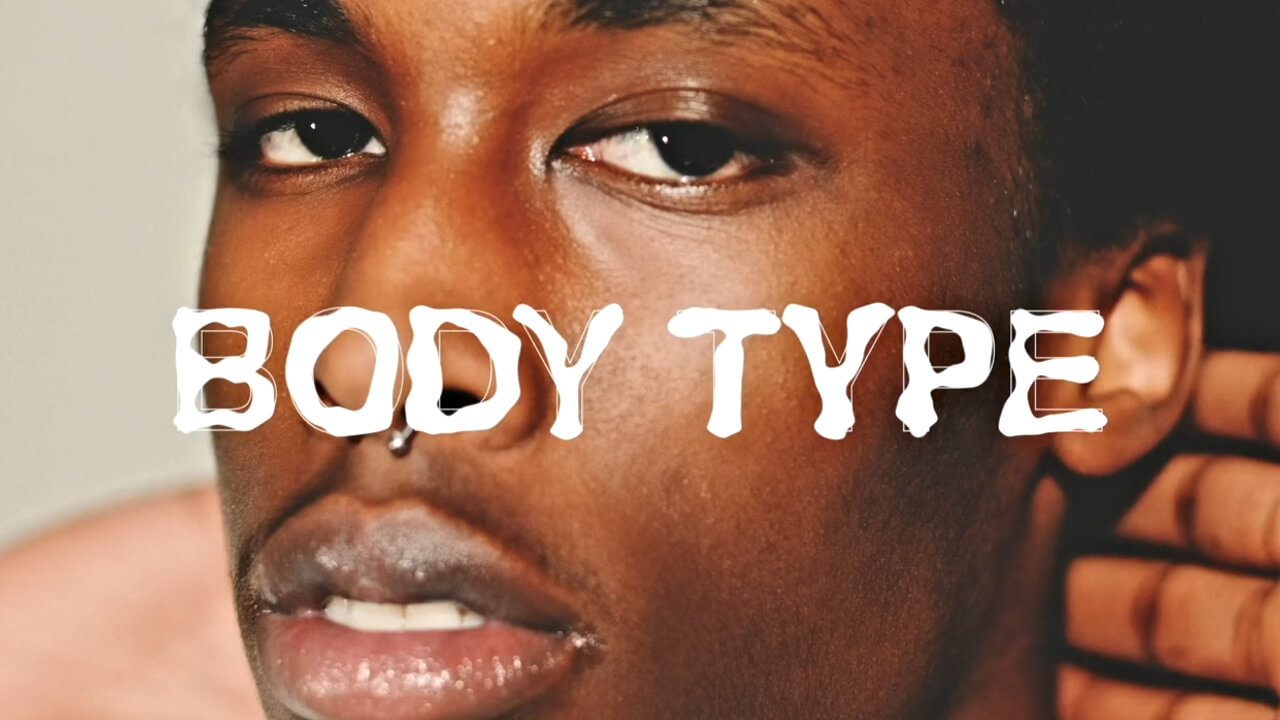
La belleza ha estado marcada históricamente por unos cánones concretos, que se han ido estrechando a raíz de la globalización y la expansión de los medios de comunicación. Una tendencia que ha generado muchas inseguridades en las personas que, en mayor o menor medida, se han preocupado por entrar en las exigencias de “lo ideal”.
La expresividad de los usuarios en el baile definirían la forma de las letras
No obstante, en los últimos años muchas marcas de moda han apostado por romper con estos cánones y mostrar toda la belleza que hay en lo natural. Siguiendo esta línea, la Miami Ad School de Hamburgo ha presentado “Body Type”, una iniciativa para Google y HMCT con toda una campaña diseñada para defender la autenticidad de los cuerpos y sus diferencias, reflejándolo a través de la tipografía.
La idea busca crear una plataforma con la que cualquier usuario pueda generar su propia tipografía, inspirada en su figura y expresividad corporal. Los usuarios accederían a la web, indicarían cuál es el principal motivo de sus inseguridades, una canción con la que se sientan identificados y, por último, mostrarían su personalidad bailando el tema seleccionado. El movimiento y expresividad del cuerpo marcarían su línea tipográfica.
La acción también incluiría la descarga de la tipografía y la posibilidad de crear productos personalizados con la nueva fuente: portadas para vinilos, camisetas, calcetines, riñoneras...
Además, también se fomentaría la difusión mediante cartelería que los usuarios se encontrarían por la calle, pudiendo escanear las imágenes para ver cómo las letras adquieren su forma característica o animarse a crear la suya propia.
“Body Type es la celebración de tu cuerpo y de la música que te hace sentir seguro”, resaltan los creadores de la iniciativa. Una manera de defender que la belleza no tiene nada que ver con parámetros ni perfecciones.